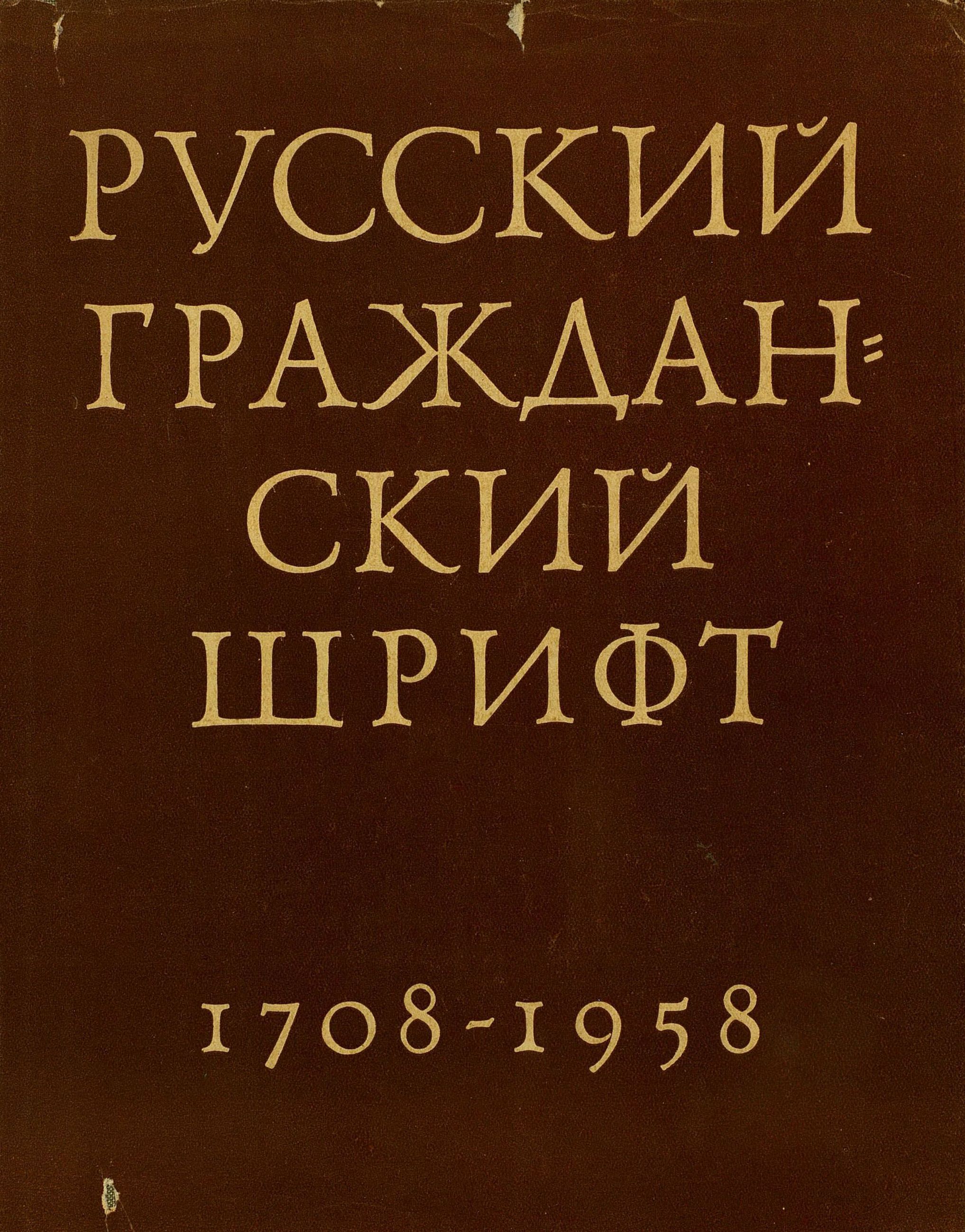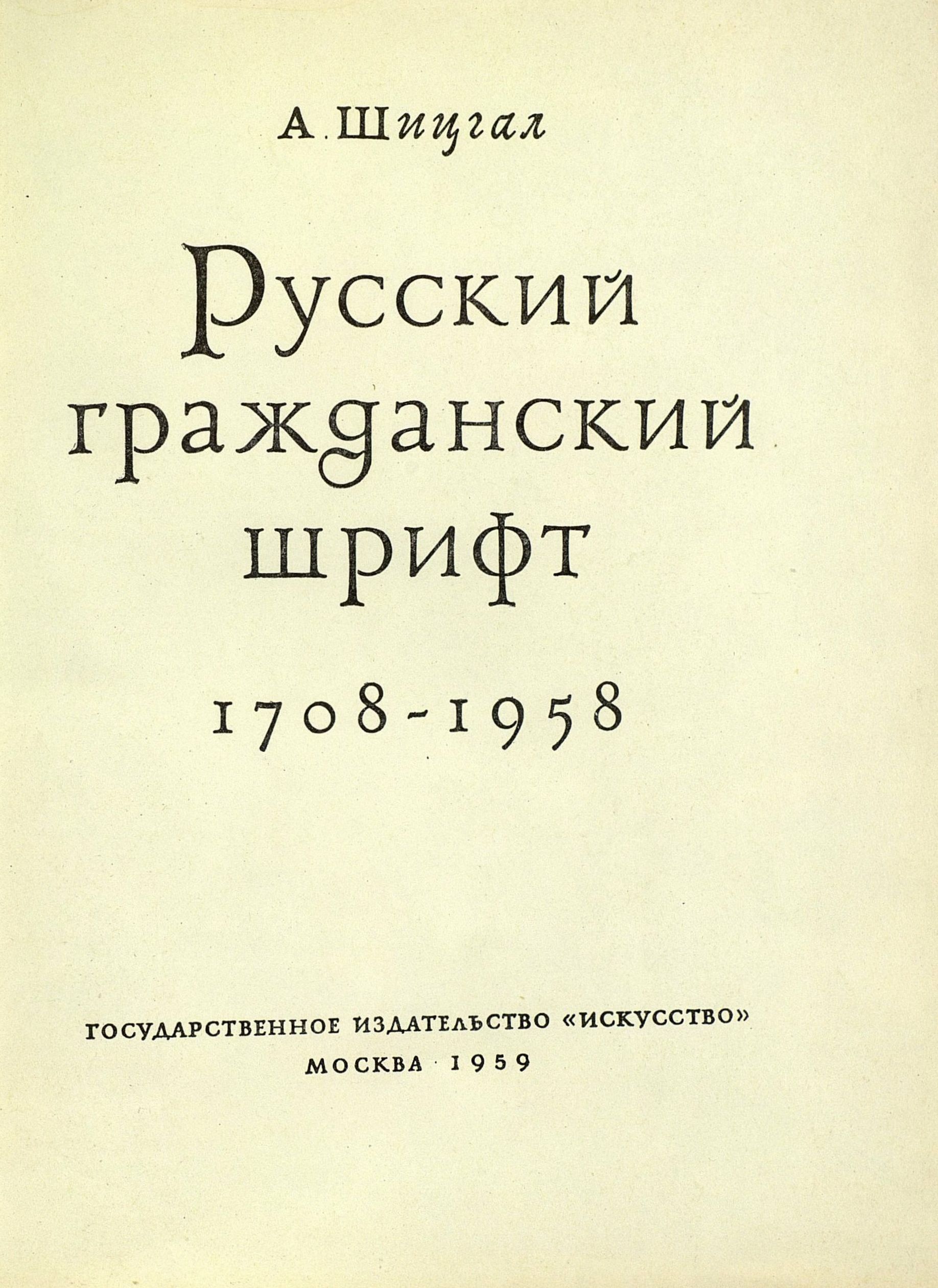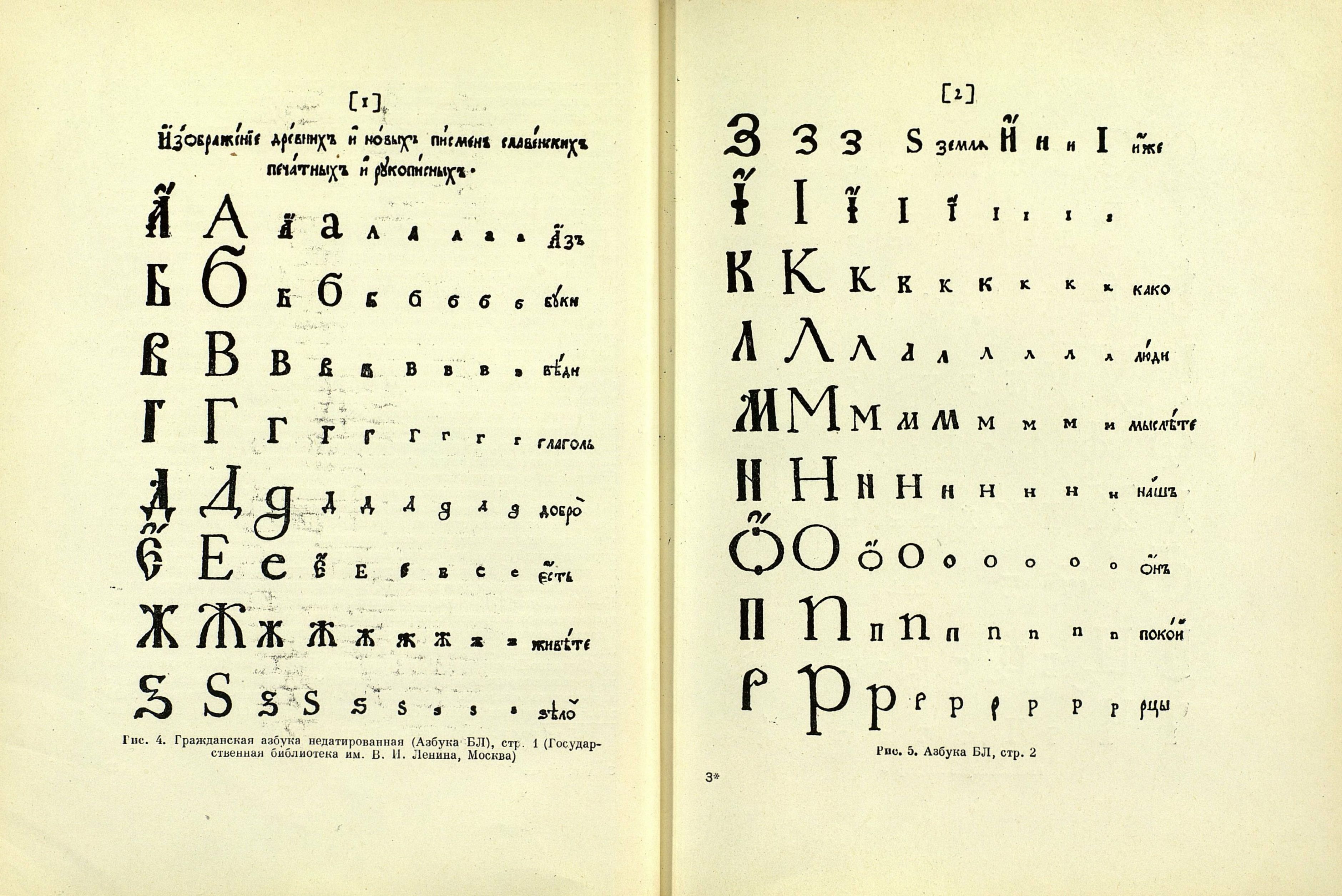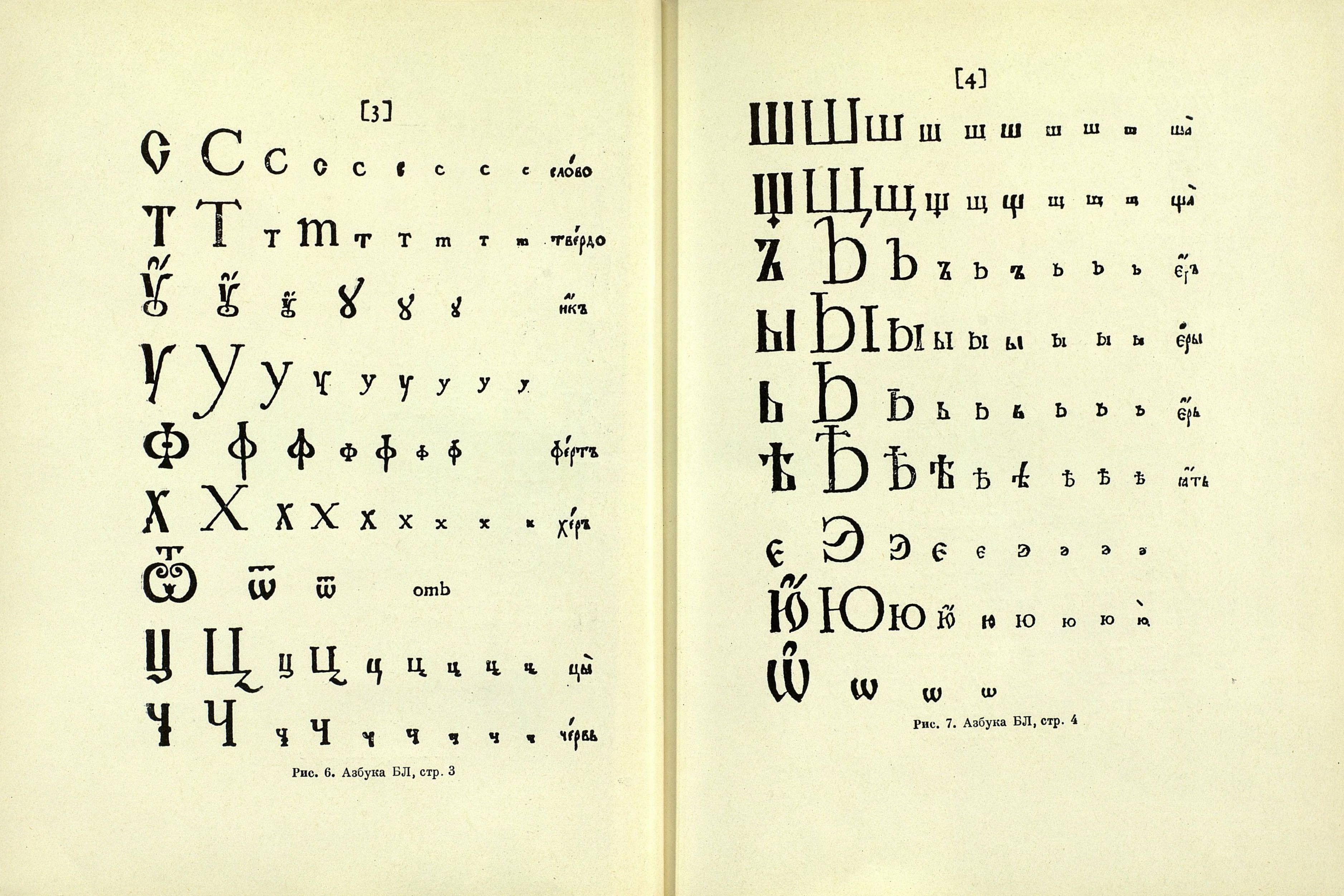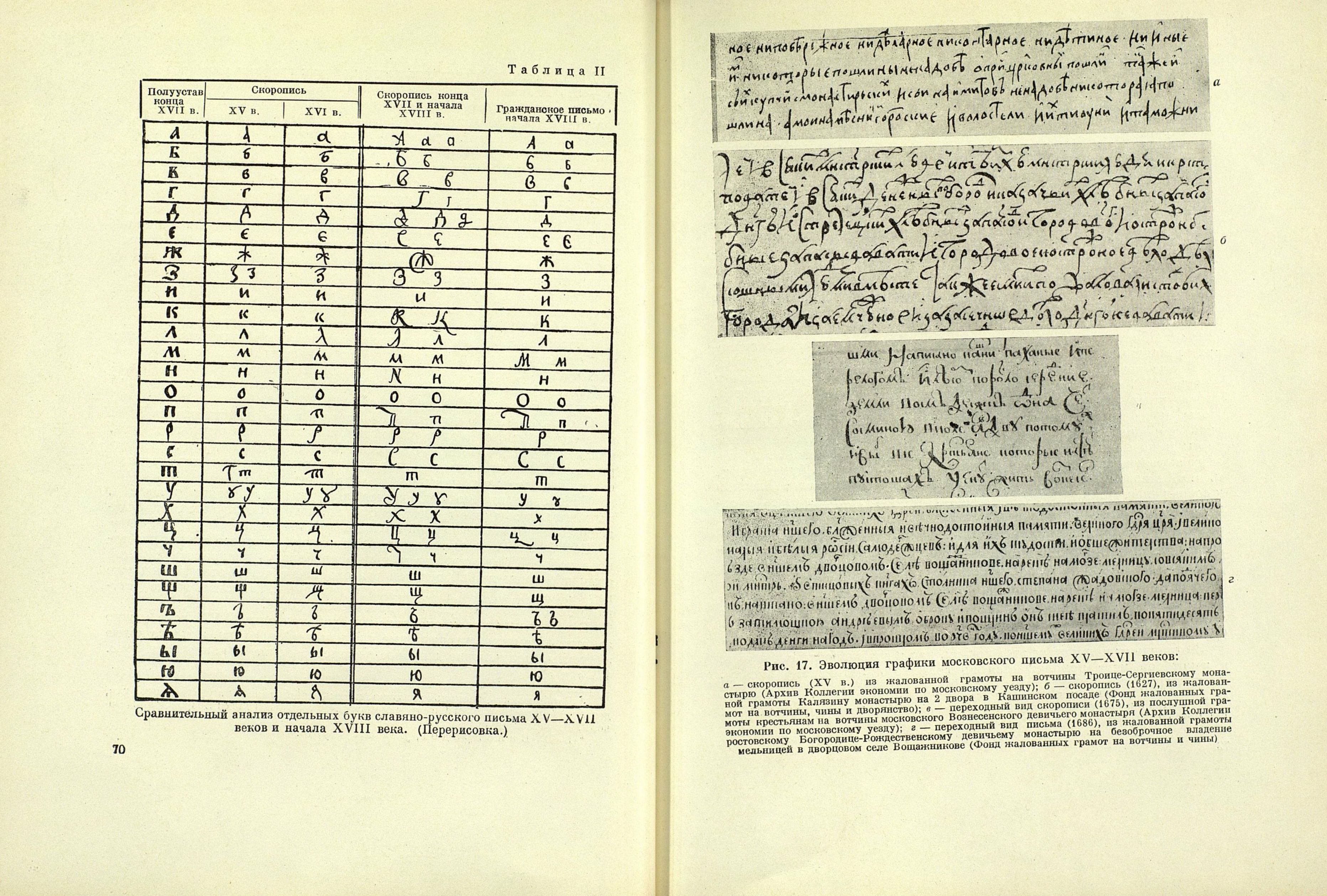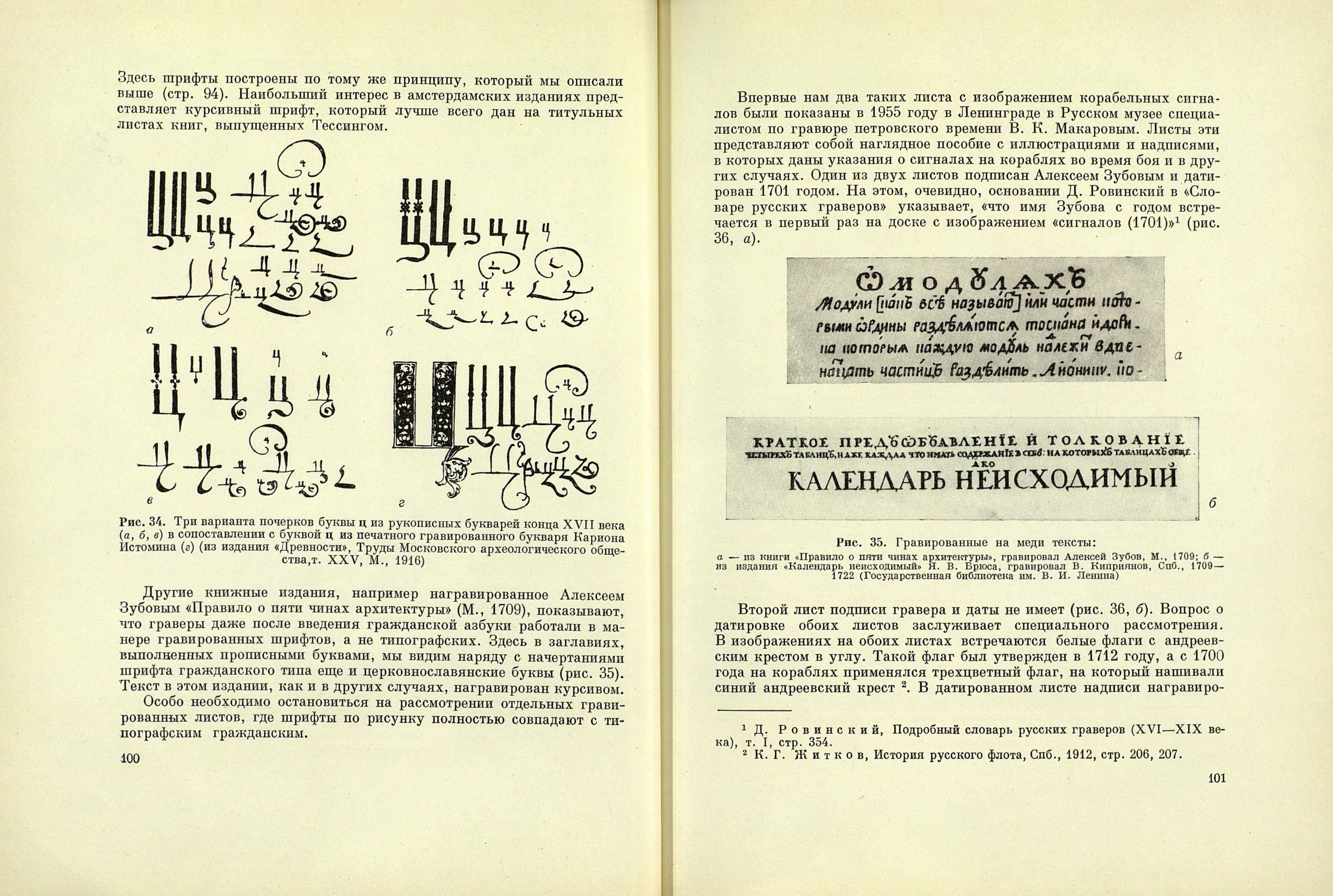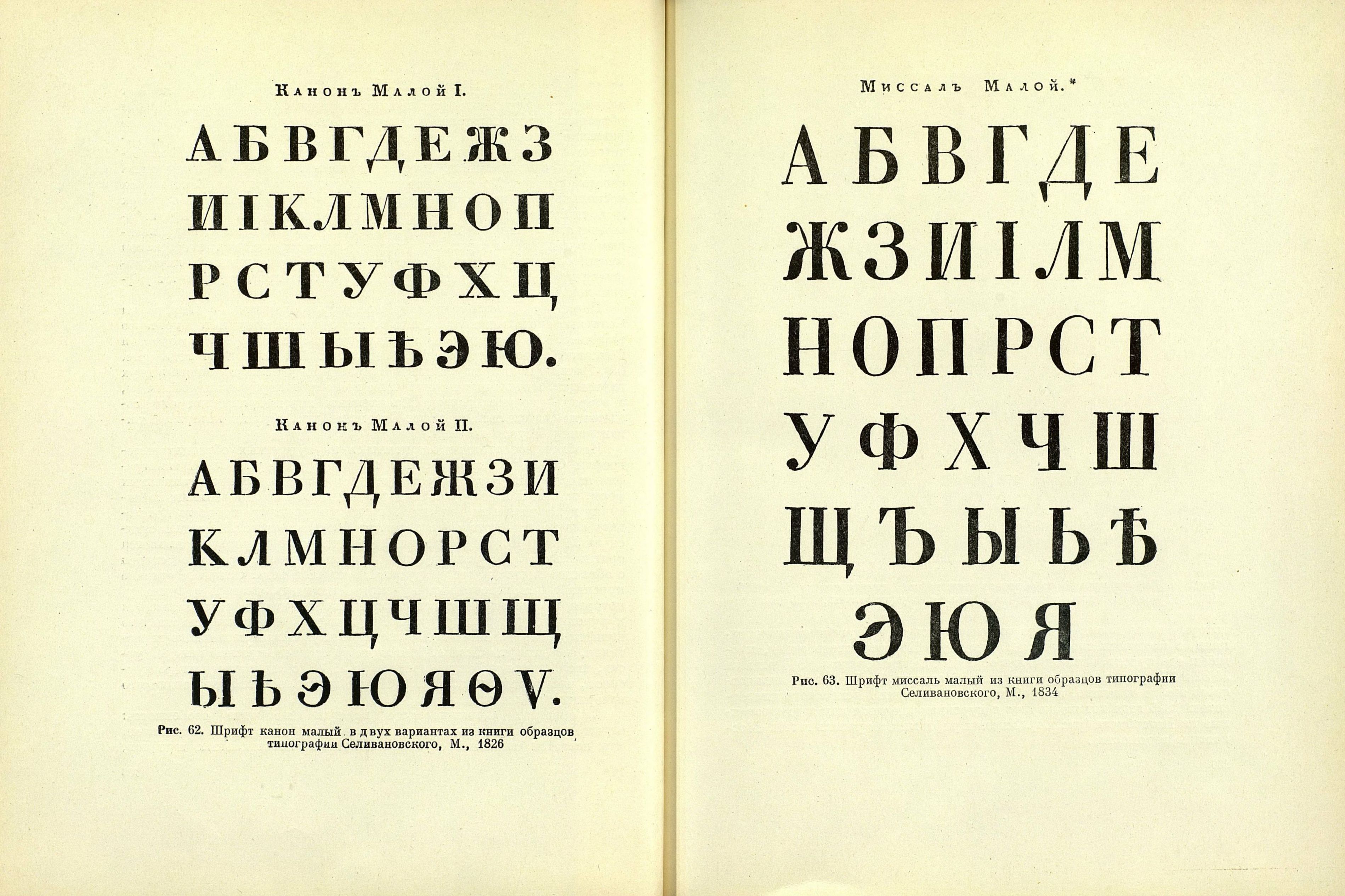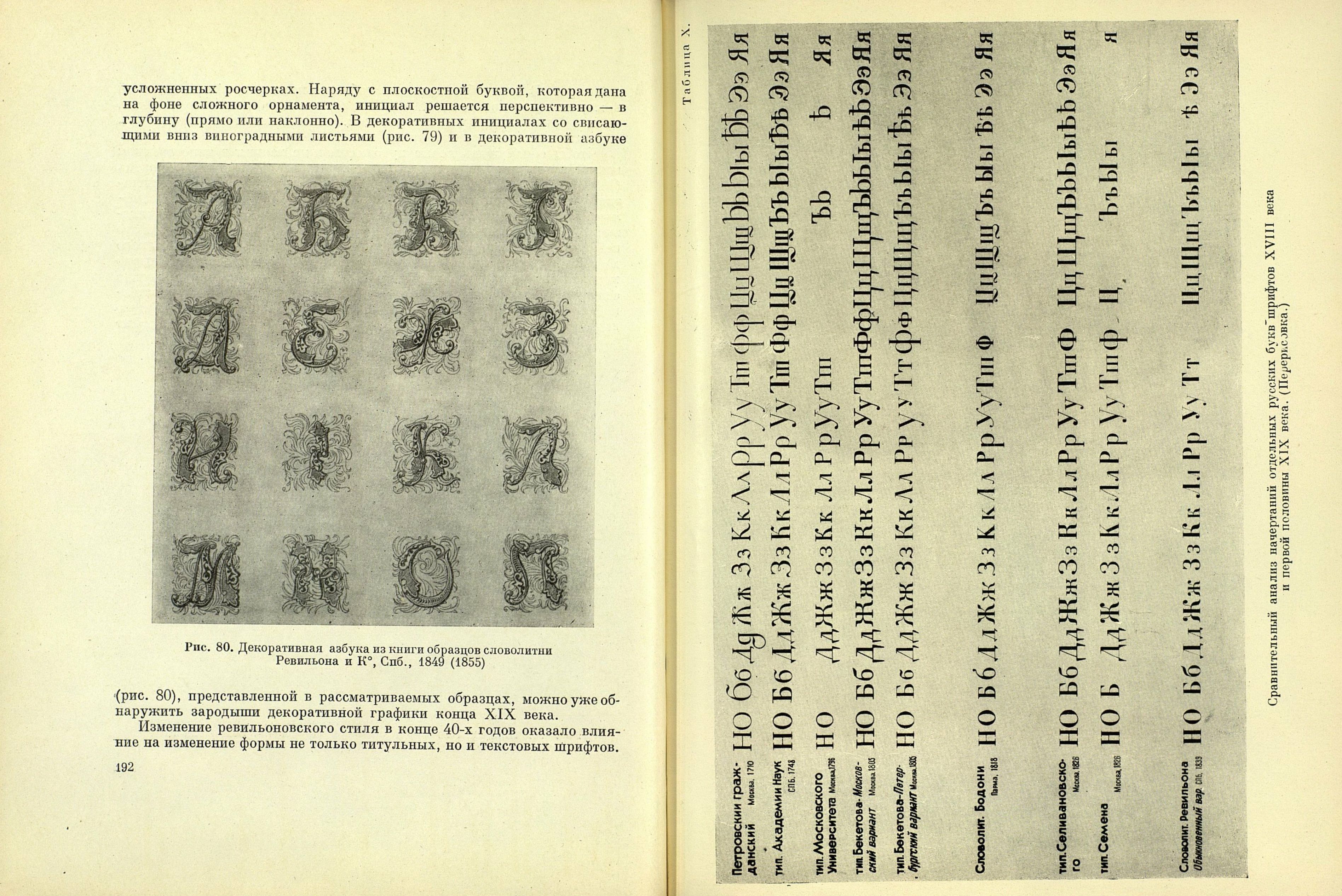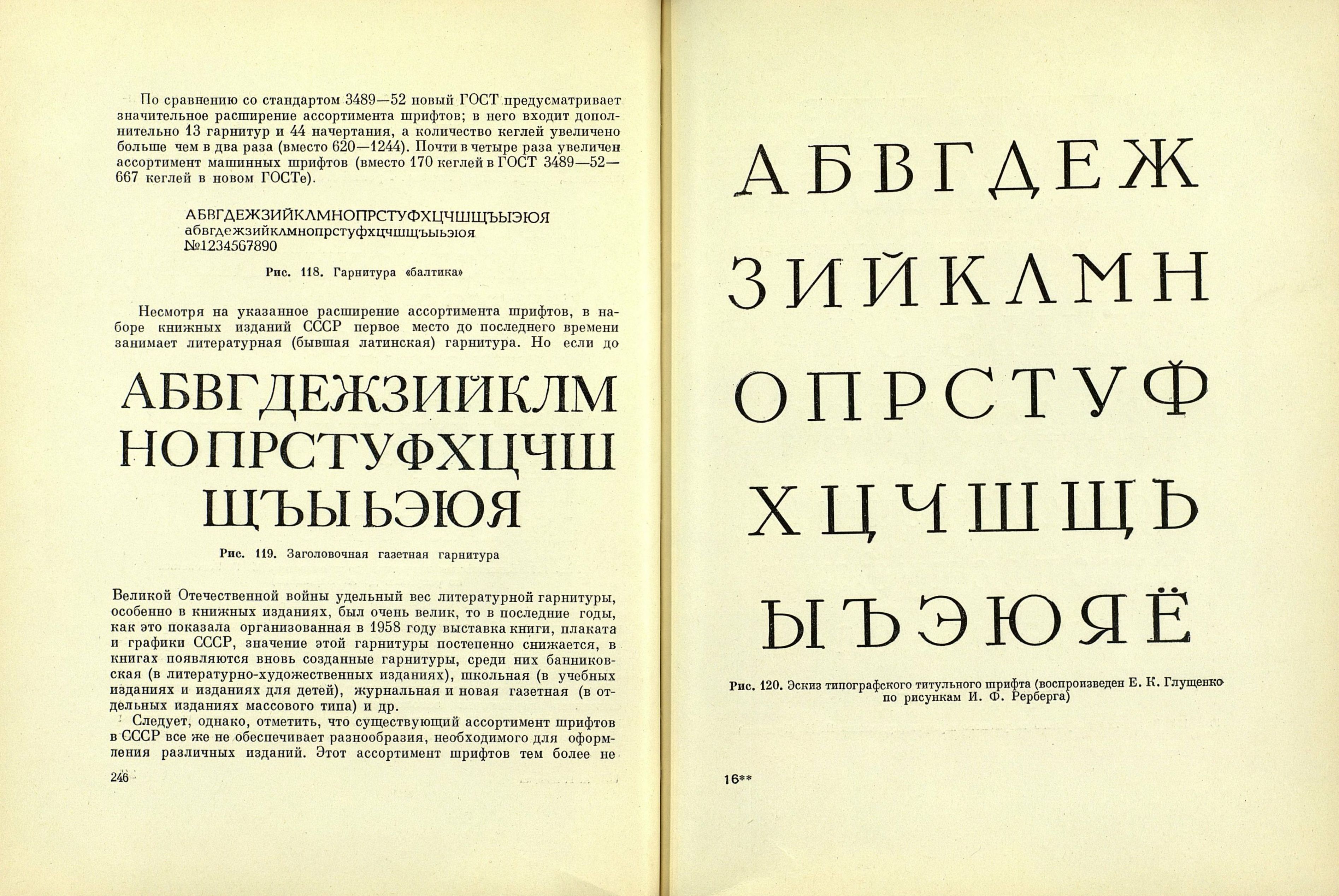
В Москве на Печатном Дворе 17(28) марта 1708 года была закончена печатью «Геометриа славенски землемерие» — первая книга, набранная вновь созданным гражданским шрифтом.
Исполнилось 250 лет существования русского гражданского шрифта, графика которого легла в основу письменности большинства народов Советского Союза, а также болгарской и сербской письменности.
Создание в начале XVIII века гражданского шрифта составило эпоху в развитии русской культуры. Шрифт благодаря реформе стал гораздо проще и доступнее широким кругам населения. Чрезвычайно важным при разработке гражданской азбуки было исключение знаков ударений, сокращений, а также введение арабских цифр вместо обозначения чисел буквами, затруднявшими арифметические действия.
«Введение русской гражданской азбуки, — пишет академик В. В. Виноградов, — обозначало упадок церковно-книжной культуры средневековья, утрату церковнославянским языком господствующего положения в структуре русского литературного языка — и вместе с тем намечало пути дальнейшей борьбы за создание на народной основе национально-русского литературного языка»1.
Между тем до последнего времени многие вопросы происхождения очень важного памятника русской культуры — петровской гражданской азбуки и особенно ее развития — оставались неисследованными и в научной литературе получили недостаточное освещение.
Началом изучения гражданского шрифта можно считать появление труда В. К. Тредиаковского «Разговор... об ортографии»1, вышедшего в 1748 году. В своей книге Тредиаковский, известный широким кругам читателей как ученый и поэт допушкинского времени, подробно рассматривает гражданскую азбуку2 с точки зрения русского правописания. Несмотря на то, что Тредиаковский был почти современником введения гражданского шрифта, он, по собственному признанию, не много знал о происхождении нового шрифта. Тредиаковский был осведомлен, что образец рисунка гражданского шрифта был послан для изготовления литер в Амстердам. Однако «О годе, в котором оный образец послан в Голландию, — пишет Тредиаковский, — мне неизвестно: не мог я сего нигде доискаться, и ни у кого доспроситься, сколько ни трудился. О сем только уведомился, что новая азбука привезена в Москву не прежде 1708 года»3. Оценивая графику новой азбуки, Тредиаковский писал: «Самая главная причина к изобретению нашего гражданского типа было желание, чтоб нашим буквам быть, сколько возможно, подобным буквам нынешним латинским»4. В этом Тредиаковский был неправ. Как мы увидим ниже, не эту цель ставили себе создатели азбуки; гражданский шрифт построен прежде всего на основе графики кирилловского московского письма конца XVII и начала XVIII века.
2 Значение слова «азбука» в XVII и первой половине XVIII века было двояким: «азбука» как алфавит определенной системы письма, «азбука» как шрифт определенного размера или рисунка. В настоящей работе мы пользуемся этими двумя значениями слова «азбука».
В связи с тем, что первопечатная «Геометрия» вышла в свет с большим опозданием5 из-за вклеек, которые не были готовы, Тредиаковский неправильно считал, что первая книга, набранная гражданским шрифтом, была «Приклады како пишутся комплементы разные»; эта книга фактически была напечатана после «Геометрии», в апреле 1708 года.
В майском номере московского периодического издания «Библиотеки для чтения» за 1834 год был опубликован первый документ, в котором излагалось содержание ныне широко известного указа Петра I от 1 января 1708 года, в котором сообщается о приезде из Амстердама в Москву «книжного печатного дела мастеровых людей» и привозе ими «новоизобретенных русских литер», которыми велено было «напечатать Геометрию и иныя гражданский книги»6. Полный текст подлинного документа этого указа был опубликован известным библиографом П. Строевым в 1841 году в его книге «Описание старопечатных книг славянских»1.
____________
6 «Библиотека для чтения», М., 1834, май, т. III, ч. 2, Отд. VI Литературная летопись, стр. 38.
1 П. Строев, Описание старопечатных книг славянских, М., 1841, стр. 250.
Важным этапом в изучении рассматриваемого вопроса явилось известное двухтомное исследование академика П. Пекарского «Наука и литература в России при Петре Великом»2. В этой работе дается описание книг и подробно освещается издательская деятельность петровского времени, приводятся документы и материалы о происхождении гражданской азбуки. Однако автор затрагивает в своем труде преимущественно вопросы, связанные с изготовлением литер нового шрифта в Амстердаме и с буквенным составом азбуки; параллельная работа по изготовлению литер, которая проводилась в Москве, Пекарскому осталась неизвестной. Что касается графики азбуки, то Пекарский придерживался в этом вопросе мнения Тредиаковского.
____________
2 П. Пекарский, Наука и литература в России при Петре Великом (тт. I—II), Спб., 1862.
Весьма важные документы о создании гражданского шрифта были опубликованы сотрудником Московского синодального архива Н. Н. Григоровичем в 1877 году3.
____________
3 Н. Григорович, Азбука гражданская с нравоучениями, правлена рукою Петра Великого, Спб., 1877 (то же в издании Общества любителей древней письменности, № 78, Прилож. к статье VIII, Спб., 1877).
Первый документ — это факсимильно переизданная учебная «Азбука» 1710 года с исправлениями Петра I4. Второй документ — известная челобитная словолитца Михаила Ефремова на имя царя — частично раскрывает работу московских словолитцев по нарезке и отливке литер гражданского шрифта и содержит оттиски со шрифтов, нарезанных Михаилом Ефремовым с другими словолитцами5.
____________
4 Оригинал азбуки с корректурой Петра I хранится в Центральном Государственном историческом архиве в Ленинграде (ЦГИАЛ).
5 Челобитная Михаила Ефремова была найдена инспектором Московской синодальной типографии В. Е. Румянцевым в архиве библиотеки Печатного Двора.
Н. Григорович вопреки документу, опубликованному Строевым в 1841 году, пришел к выводу, что первопечатная «Геометриа» набрана шрифтом, отлитым Михаилом Ефремовым. Эта ошибка, к сожалению, повторялась вслед за Григоровичем долгое время в работах различных авторов6.
____________
6 См. Ф. И. Булгаков, Иллюстрированная история книгопечатания, Спб., 1889, стр. 306; Я. Б. Шницер, Иллюстрированная всеобщая история письмен., Спб., 1903, стр. 236; А. Н. Соловьев, Государев Печатный Двор и синодальная типография в Москве, М., 1903, стр. 56.
Повышенный интерес к вопросам, касающимся происхождения русского гражданского шрифта, был связан с отмечавшимся впервые в России в марте 1908 года юбилеем по случаю двухсотлетия гражданского шрифта. Юбилей этот был ознаменован специальными докладами и выставками печатных произведений в Московской синодальной типографии и в Русском библиографическом обществе при Московском университете.
В Московской синодальной типографии старшим справщиком А. Н. Соловьевым1 был сделан доклад, опубликованный затем отдельным изданием в качестве исторической справки (без указания автора)2. В этой работе дана сводка известных до того времени сведений о гражданском шрифте.
____________
1 «Московский листок» от 18 марта № 65, 1908 год.
2 «Двухсотлетие русской гражданской азбуки» (1708—1908), Московская синодальная типография, М., 1908.
Иной характер имели доклады, зачитанные 8 марта 1908 года в Русском библиографическом обществе при Московском университете членами общества: В. И. Покровским на тему «Книга и читатель 200 лет назад» и профессором-филологом Р. Ф. Брандтом — «Петровская реформа азбуки»3. В них явно сказывается реакционная тенденциозность авторов.
____________
3 Доклады были опубликованы отдельным изданием «Двухсотлетие гражданского шрифта», М., 1910.
В докладе В. И. Покровского говорится не о роли, которую сыграли в развитии русской науки и просвещения научные издания и учебные пособия, выпущенные впервые в петровское время, а, наоборот, подчеркивается, что «любимейшей книгой для чтения искони и до наших дней является псалтирь... Во время Петра, — утверждал Покровский, — зачитывались ею»4. Профессор Брандт, в свою очередь, меньше всего говорил о значении введения гражданского шрифта для развития русской печати. «Жаль, — восклицал он, — что не остались при славянском (т. е. церковнославянском.— А. Ш.) шрифте»5.
____________
4 Там же, стр. 20.
5 Там же, стр. 42.
Эти реакционные установки не встретили отпора в русской дореволюционной литературе.
С принципиально иных позиций подошли, естественно, к оценке реформ кирилловского полуустава Петром I советские исследователи. В тесной связи с содержанием и оформлением новых изданий гражданский шрифт рассматривается в труде члена-корреспондента Академии наук СССР А. А. Сидорова, освещающем историю оформления русской книги6. Среди работ советских авторов надо указать статьи старшего научного сотрудника Н. П. Проскурнина7, который в Архиве Московской синодальной типографии обнаружил ряд важных документов, относящихся к происхождению гражданской азбуки. Н. П. Проскурнин устанавливает, в частности, дату начала набора гражданскими литерами, приводит подлинный титульный лист «Геометрии» и другие материалы.
____________
6 А. А. Сидоров, История оформления русской книги, М., 1946.
7 Бюллетень технико-экономической информации Научно-исследовательского института полиграфического машиностроения, 1953, №№ 33, 34; 1954, № 37 (литографированное издание).
Из найденных в советское время документов особый интерес представляют 11 страниц учебной азбуки с образцами шрифтов, обнаруженных в 1944 году библиографом Е. И. Кацпржак в собрании старопечатных книг Котельникова, приобретенном Всесоюзной библиотекой им. В. И. Ленина после Октябрьской революции1. Согласно Н. П. Проскурнину, печать первых восьми страниц этой азбуки датируется апрелем 1708 года2. Азбука, обнаруженная в библиотеке им. В. И. Ленина, равно как оттиски шрифтов Михаила Ефремова и азбука 1710 года, являются исключительно ценными материалами, на основе которых представляется возможным установить корректуры шрифта, проведенные Петром I на различных этапах, а также уточнить рисунки и размеры шрифтов литер, привезенных из Амстердама и изготовленных в Москве.
____________
1 Е. И. Кацпржак, Первые образцы русских типографских шрифтов, «Полиграфическое производство», 1950, № 5.
2 Н. П. Проскурнин, Ценная находка, газета «Советская культура», 1953, № 65.
В 1947 году автором настоящей книги была опубликована работа «Графическая основа русского гражданского шрифта», в которой рассмотрены вопросы графики гражданской азбуки во взаимодействии с московским кирилловским письмом конца XVII и начала XVIII века»3 и показаны основные ошибки, которые допускались в прошлом в трактовке графической основы гражданской азбуки. Эти ошибки определялись главным образом неразработанностью классификации почерков в русской палеографии.
____________
3 А. Г. Шицгал, Графическая основа русского гражданского шрифта, М., 1947.
Ценные данные по хронологии введения гражданского шрифта даны в статье Т. А. Быковой4 на основе документов, опубликованных в многотомном издании «Письма и бумаги императора Петра Великого»5.
____________
4 Т. А. Быкова, Первые образцы гражданских шрифтов (Описание изданий гражданской печати), АН СССР, М.—Л., 1955, стр. 534.
5 Письма и бумаги императора Петра Великого, тт. IV—VI, Спб., 1900—1912; тт. VII—X, АН СССР, М.—Л., 1918—1956; в дальнейшем это издание обозначается ПБПВ.
Всего вышло десять томов указанного издания (шесть томов — в дореволюционное время и четыре последних тома — в советское время). В нем (начиная с четвертого тома) приводятся многочисленные документы, дающие возможность проследить различные этапы развития гражданского шрифта. Надо специально отметить, что этот ценный источник не был достаточно использован историками русской письменности.
До последнего времени не был известен художник (вернее, рисовальщик) азбуки, недостаточно ясен был ассортимент шрифтов по рисунку и размеру (амстердамского и московского изготовления), который применялся в гражданской печати. Недостаточно были изучены такие важные документы, как корректуры рисунков букв, проведенные лично Петром I.
Несколько замечаний по вопросам терминологии. В литературе иногда система славяно-русского письма — кириллица противопоставляется гражданскому шрифту1. Это неверно.
____________
1 См., например, Т. А. Быкова, Первые образцы гражданских шрифтов (Описание изданий гражданской печати), М.—Л., 1955, стр. 535.
Кириллицу можно рассматривать как особое начертание только при сопоставлении ее с глаголицей. Устав, полуустав, скоропись, гражданское письмо — почерки кирилловского письма, кириллица же есть система славяно-русского письма, которая с некоторыми изменениями ее буквенного состава существует до настоящего времени. Типично славяно-русские буквы, как, например, ж, ч, ц, ш, щ, ю, ъ, ь, ы, изобретенные еще в середине IX века, существуют, как известно, в нашем алфавите по сей день.
Шрифт — это графическая форма букв определенной системы письма. Поэтому нам представляется, что гражданский шрифт, созданный на основе новой графики кирилловского московского письма конца XVII и начала XVIII века и латинского шрифта антиква, является вместе с тем дальнейшим развитием системы славяно-русского письма кириллицы, буквенный состав которой (в отличие от состава букв, например, латинского алфавита) лучшим образом соответствовал звуковому составу русского языка.
Противопоставление кириллицы гражданскому шрифту приводит к тому, что гражданский шрифт рассматривают не как новый шрифт, а как новую систему письма, что явно противоречит фактам.
Следует остановиться и на вопросе о наименованиях нового шрифта. Последний, появившийся в начале XVIII века, в противовес старославянскому, которым набирались в основном церковные книги, получил название «гражданский» — в связи с новым назначением шрифта, поскольку им набирались и печатались светские книги.
В труде «Русская техническая литература первой четверти XVIII века» В. В. Данилевский предлагает для гражданского шрифта новое название — «народный шрифт» в связи с тем, что создатели нового шрифта «положили в основу всего дела народный опыт и ввели для печати новый шрифт, заслуживающий по всей справедливости название русского народного шрифта»1.
____________
1 В. В. Данилевский, Русская техническая литература первой четверти XVIII века, АН СССР, М— Л., 1954, стр. 65—66.
Несмотря на то, что мысль, высказанная В. В. Данилевским, правильна, нам думается, что предложенное название вряд ли может быть принято, так как народными являются не только русский шрифт, но и возникший в эпоху Возрождения латинский шрифт антиква, который используется в большинстве стран мира, и другие графические формы шрифтов, принятые в разных странах.
Термин «гражданский шрифт» следует сохранить за шрифтом, введенным у нас в начале XVIII века.
Создание гражданской азбуки включало два процесса: разработку рисунка букв нового шрифта, что являлось наиболее сложным и главным, и воплощение созданных рисунков в металле (т. е. изготовление пунсонов, матриц и литер).
К сожалению, в литературе при анализе азбуки основное внимание зачастую уделяют второму процессу, т. е. изготовлению литер, а первый процесс чаще всего выпадает из поля зрения исследователей.
Если по вопросу происхождения русского гражданского шрифта мы имели возможность назвать целый ряд литературных источников, то специальных работ, где были бы собраны систематические сведения по истории развития русского шрифта, к сожалению, не имеется.
Единственным библиографическим источником по истории русского шрифта является труд В. Я. Адарюкова2, который представляет ценность главным образом хорошим перечнем изданий образцов шрифтов, украшений и политипажей лучших русских типографий и словолитен XVIII и XIX веков.
____________
2 В. Я. Адарюков, Библиография русских типографских шрифтов, ГИЗ, М., 1924.
В предлагаемом вниманию читателей настоящем исследовании, состоящем из двух частей, освещаются вопросы происхождения гражданской азбуки и дается краткий очерк развития русского гражданского шрифта.
В первой части книги автор ставит себе задачей привести в систему все сведения о происхождении гражданского шрифта; особое внимание уделяется вопросам анализа графической основы гражданской азбуки.
Вторая часть работы посвящена истории развития русского шрифта. В связи с разнообразием и значительностью материала мы стремились, не претендуя на полноту изложения, привести факты и иллюстративный материал, отражающие лишь основные этапы развития русского шрифта.
В заключительной части книги в практических целях мы отмечаем лучшие рисунки русских типографских шрифтов XVIII и XIX веков, дополнительно включая современные рисованные шрифты советских художников и лучшие западноевропейские образцы, которые могут быть использованы художниками при создании новых типографских шрифтов, а также при оформлении различных печатных изданий.
При написании первой части книги использованы основные документы о происхождении русского гражданского шрифта, к которым относятся: «Письма и бумаги императора Петра Великого» (среди них некоторые использованы впервые) архивные материалы, в том числе из ЦГАДА (главным образом Архива Приказа книгопечатного двора)¹, гравированные листы Исторического музея и Музея изобразительных искусств им. А. С. Пушкина в Москве, Русского музея в Ленинграде и материалы фонда Всесоюзной библиотеки им. В. И. Ленина (недатированная гражданская азбука², печатные издания первой четверти XVIII века и другие).
____________
¹ Указанные материалы в порядке сквозной нумерации даны в приложении, а ссылки на эти документы обозначены в тексте арабской цифрой в скобках.
² В дальнейшем в тексте эта азбука нами обозначается «Азбука БЛ».
При написании второй части книги в качестве первоисточников использованы главным образом образцы шрифтов, политипажей и наборных украшений, а также печатные издания XVIII и XIX веков.
Автор считает своим долгом выразить благодарность сотрудникам названных выше архивов и книгохранилищ, оказывавшим ему постоянную помощь, а также Л. П. Теплову за указание ряда использованных материалов. Особенно признателен автор члену-корреспонденту Академии наук СССР А. А. Сидорову, взявшему на себя труд по рецензированию настоящей работы.
Своему старому другу, доктору исторических наук М. Г. Левину автор обязан помощью в подготовке настоящего труда к печати.
ОГЛАВЛЕНИЕ
Введение ... 5
Происхождение русского гражданского шрифта
Глава I. Основные сведения о происхождении русского гражданского шрифта ... 21
Глава II. Графика московского письма конца XVII и начала XVIII века ... 62
Глава III. Буквенный состав и графическая основа русской гражданской азбуки ... 77
Краткий очерк развития русского гражданского шрифта
Глава IV. Русские шрифты XVIII века ... 117
Шрифты Петербургской типографии Академии наук ... 117
Шрифты типографии Московского университета ... 136
Глава V. Русские шрифты первой половины XIX века ... 146
Шрифты московских типографий ... 146